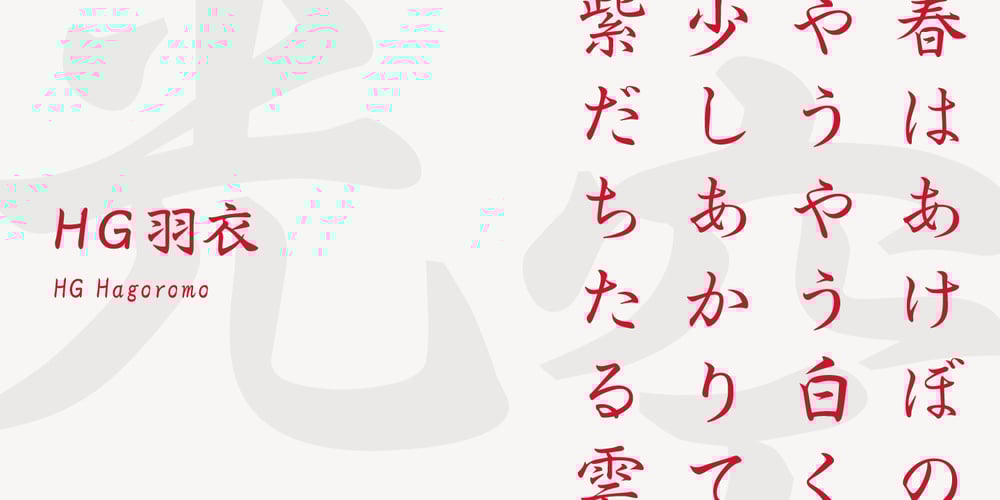
HG Hagoromo
HG Hagoromo font
HG Hagoromo Font Family was designed by published by RICOH. HG Hagoromo contains 4 styles and family package options. 羽衣は、大谷四郎氏によって楷書体と行書体との中間を目指して作られました。楷書の堅さと行書の柔らかさがバランスよく配分されていて、どちらかというとやや楷書寄りのデザインです。楷書体に脈絡線やはね、はらいが加えられたようなデザインになっています。また、行書体ではストロークを繋げたりして省略されている部分を、可能な限り省略しない処理をしています。やや長めの文章から見出しまでフォーマルな場面に向きます。 (『OH 「羽衣」書体について』より一部抜粋)